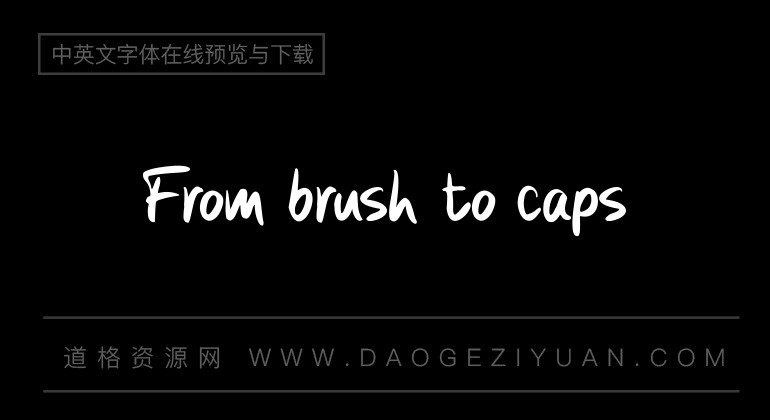
From brush to caps
From brush to caps 是一款拥有古典复古风格的手写字体,它拥有浓浓的古典复古风格,字体的笔触柔和而又充满了活力,它可以用于海报、印刷品、品牌形象等。它的特点是有着温暖的笔触,更具有细腻的细节和视觉效果,能够为您的作品带来温暖的感觉。它的字形设计简洁大方,可以满足您的各种设计需求,为您的作品增添更多的色彩。
From brush to caps是一款非常不错的手写艺术字体,具有很好的视觉感,适合于文化类的宣传设计、商业类品牌的广告和产品包装设计以及个性化文字排版等较多场景。